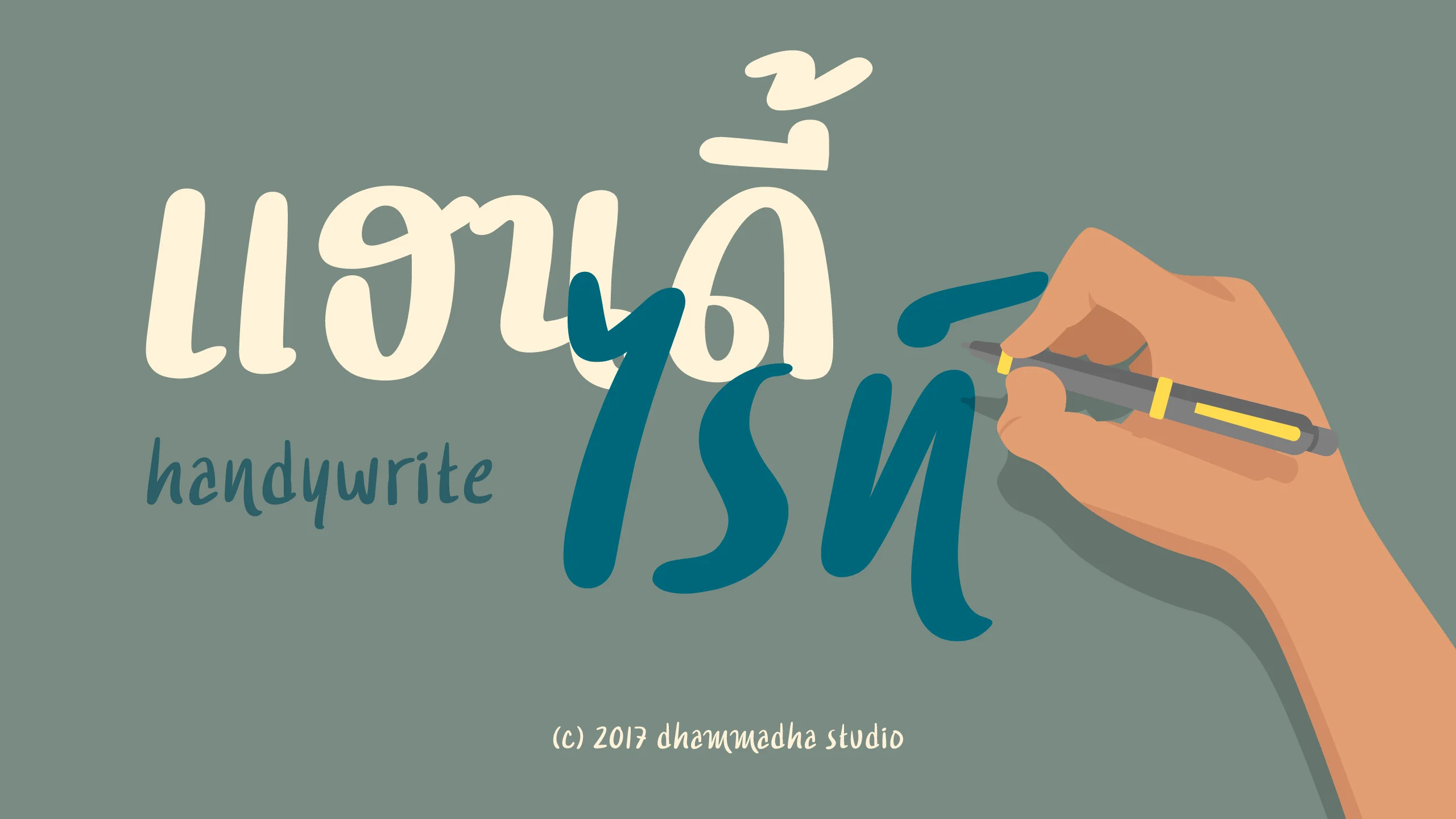
handywrite
การตีความลายมือในรูปแบบที่ดูเป็นธรรมชาติและมีความเป็นกันเองมากขึ้น โดยต่อยอดความสำเร็จจากความละมุนของฟอนต์ชุดก่อนหน้า สู่การสร้างสรรค์ลายเส้นที่มีความอิสระและดูสมจริงผ่านส่วนผสมที่ลงตัว ระหว่างน้ำหนักปากกา Wacom และหัวแปรงแบบ Brush เราตั้งใจรักษาเสน่ห์ของความ 'ดิบ' และจังหวะการลากเส้นที่ให้ความรู้สึกเหมือนการเขียนด้วยมือลงบนกระดาษจริงๆ ก่อนจะนำมาเกลาโครงสร้างให้ดูเข้าที่ เพื่อให้ได้ฟอนต์ที่มีบุคลิกโดดเด่นแต่ยังคงความสมดุลในทุกมุมมอง เพื่อให้ลายมือดิจิทัลชุดนี้สื่อสารได้อย่างเป็นธรรมชาติที่สุด เราได้เพิ่มลูกเล่นของอักษรควบ (Ligature) และฟังก์ชัน Script ที่ครบถ้วนลงไป ช่วยลดทอนความแข็งกระด้างและเพิ่มความลื่นไหลประดุจงานเขียนจริง "แฮนดี้ไรท์ | handywrite" จึงเหมาะอย่างยิ่งสำหรับงานออกแบบที่ต้องการความ Unique และมีตัวตนที่ชัดเจน ไม่ว่าจะเป็นงานคอนเทนต์สไตล์ไลฟ์สไตล์ การออกแบบบรรจุภัณฑ์ หรืองานกราฟิกที่ต้องการเปลี่ยนข้อความธรรมดาให้ดูมีชีวิตชีวาและเข้าถึงง่ายในทันที